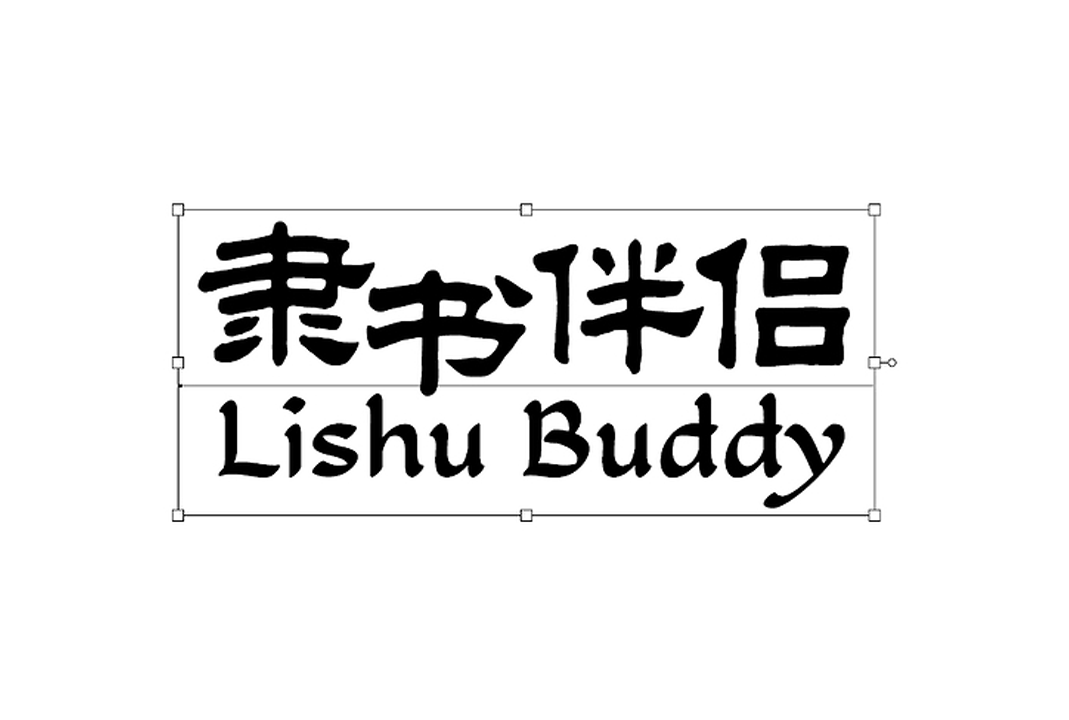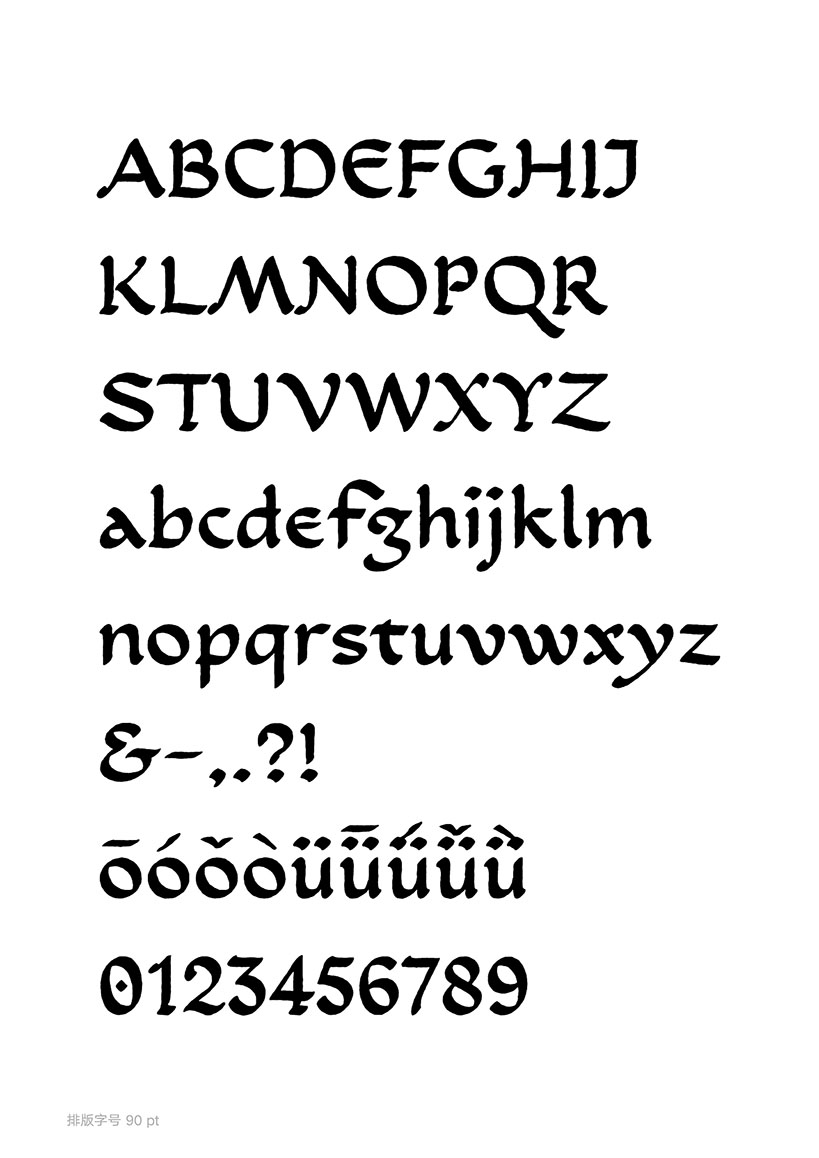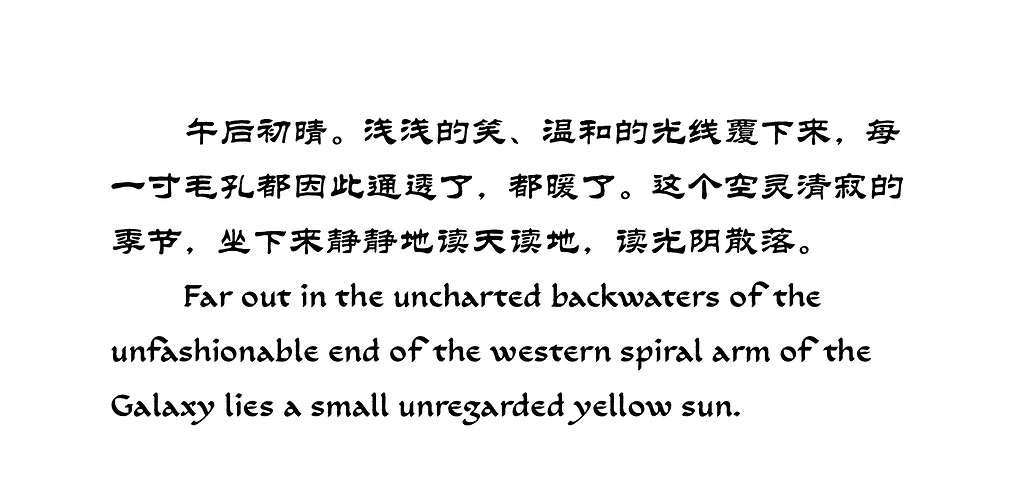
隶书伴侣(LishuBuddy)是由站酷设计师figovision(UID:1042506)创作的一款免费可商用英文字体。该字体通过系统性调整中西隶书文字形的视觉特征,实现了二者在混排时的气质融合,这在日常隶书使用中西文混排场景时尤为重要。
1、字形结构偏扁宽,笔画粗细对比较为均匀,与隶书的气质协调,版面灰度均衡;
2、强化西文横笔画中的波磔,甚至在一些弧线末端也进行了横向的处理,如c、d、e、k、q、s、C、E、F、G、S、J;
3、在西文设计中,使用super brush来模拟鹅毛笔的书写规律,考虑到隶书笔画横粗竖细的特点,将super brush的斜角调整为45度(常规为30度),得到较为均匀的横竖对比;
4、为配合隶书笔画的粗糙化效果,单独设计了粗糙化(rough)的style,以及单独设计了中文标点,考虑到西文字体有单独使用的场景,不能使用中文标点的字宽,因此将中文标点单独设计为独立的style,因此,本字体家族共有3款风格:regular、rough、Chinese Punctuation,可以在indesign中通过复合字体搭配使用;
5、对于这种手写字体,字间距。
该字体特别适用于需要中西文混排的设计场景,通过精密的视觉校准实现中西文排版时视觉一致的效果。